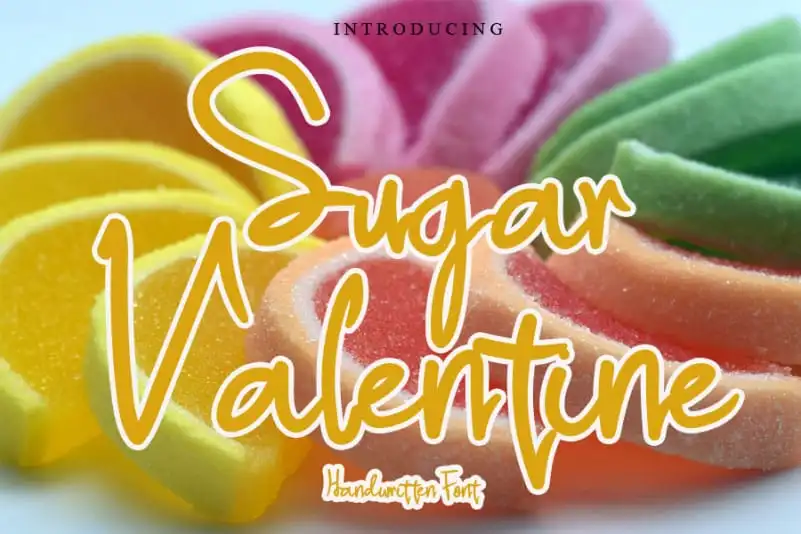
Sugar Valentine Handwritten Font – Download Grátis
Sugar Valentine Handwritten Font é uma elegante fonte escrita à mão que transmite alegria e charme. Este tipo de letra é leve e encantadora, com seu toque whimsical e um quê peculiar, tornando-o perfeito para iluminar qualquer projeto gráfico ou design. Se você adicionar Sugar Valentine Handwritten Font confiante aos seus trabalhos, certamente apreciará a beleza que ele trará às suas criações. Esta fonte é ideal para uma pausa descontraída e divertida em sua produção de design, tornando-a ainda mais única e agradável aos olhos do público.